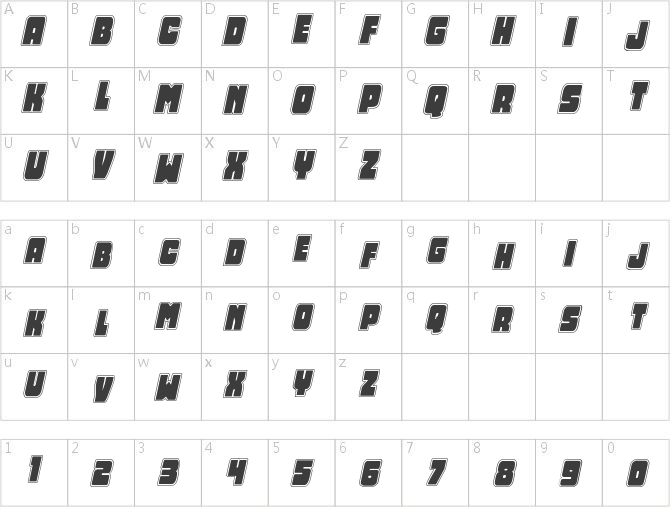
Opus Mundi Academy Italic 詳情頁
Opus Mundi Academy Italic字體字庫是一款讓人賞心悅目、百看不厭的英文字體,適合各類廣告和產(chǎn)品包裝設(shè)計應(yīng)用,字體大小0.1MB,格式為ttf字體,上傳用戶是釜源貿(mào)易,作者/版權(quán)方為未知